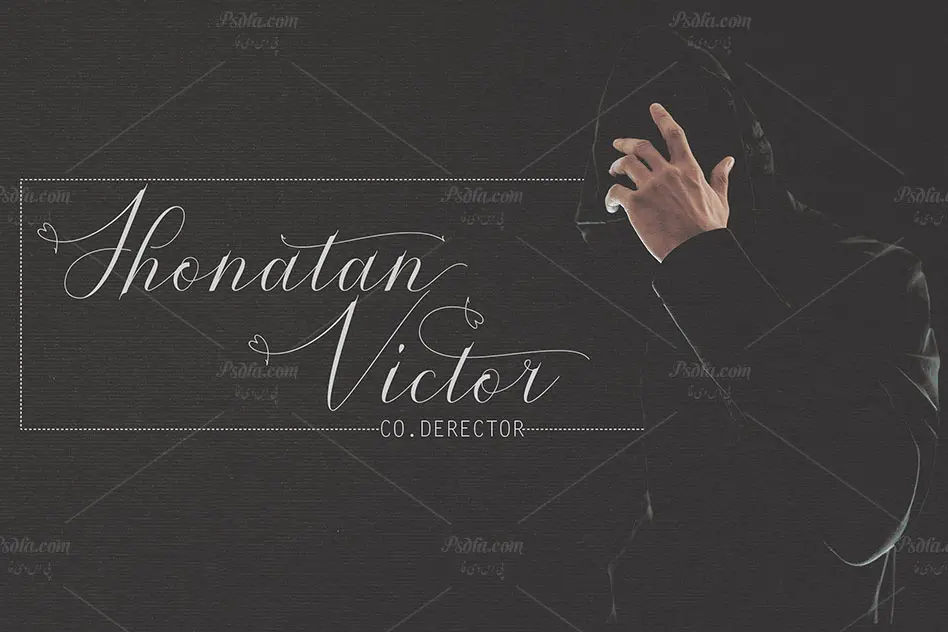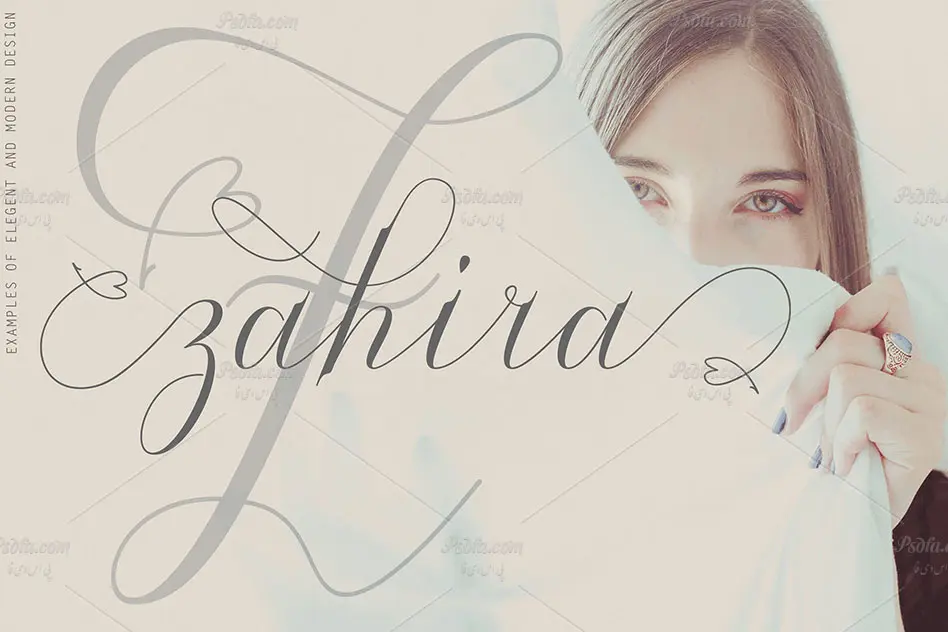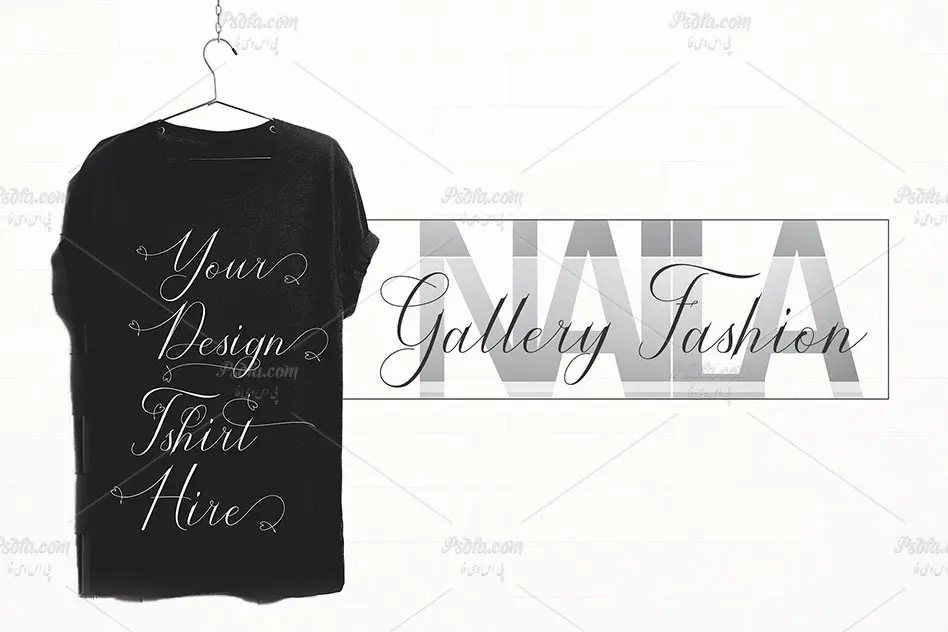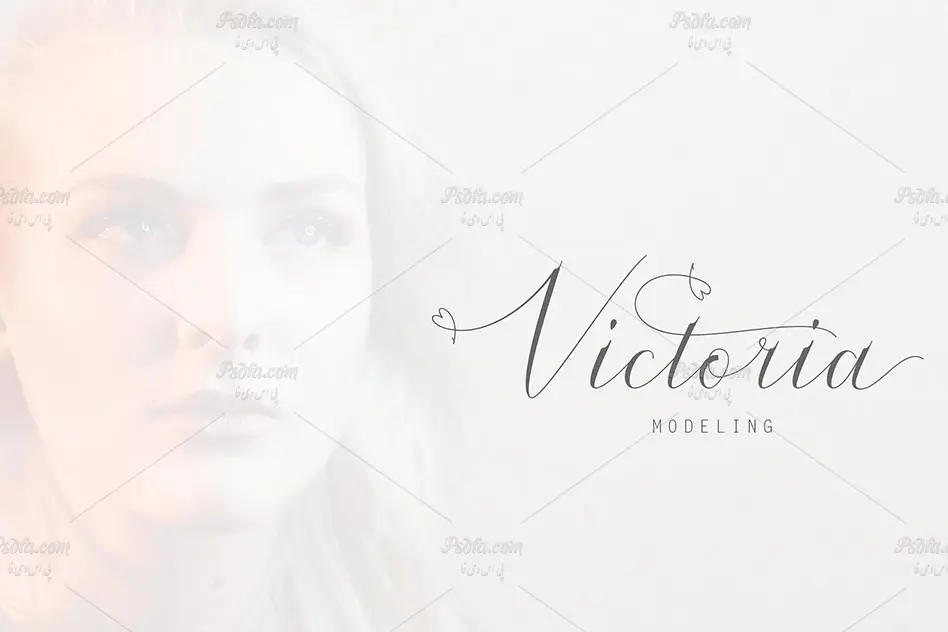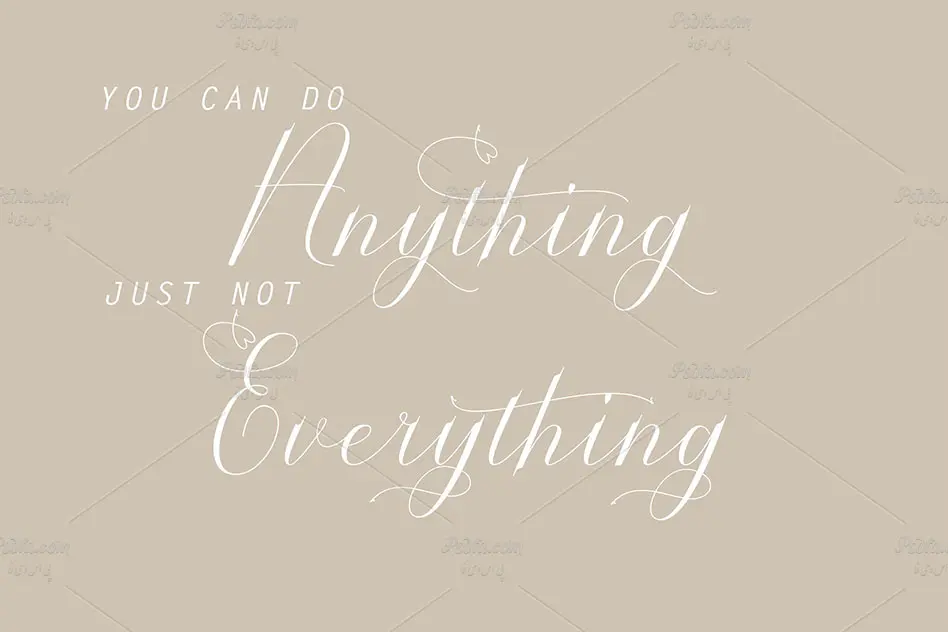
در این پست شاهد فونت دستنویس انگلیسی Serendipity مناسب جهت استفاده در طرح های گرافیکی می باشید. این فونت زیبا در قالب 2 فایل ttf و otf در سایت بارگذاری شده است که با نصب یکی از این دو فرمت در پوشه فونت های سیستم قادر به استفاده از آن در تمام نرم افزارهای گرافیکی و ویرایشگر متن از جمله نرم افزار فتوشاپ ، مجموعه نرم افزار آفیس و … خواهید بود. فونت Serendipity در وزن معمولی (Regular) طراحی شده است که از آن می توان در طرح های گرافیکی همچون طراحی انواع پوستر ، بنر ، تراکت ، بروشور ، کارت تبریک ، کارت پستال ، کارت عروسی و … استفاده نمود. همچنین نسخه وب این فونت نیز در فرمت های eot , svg , ttf , woff و woff2 در فایل فشرده قرار گرفته است که در طراحی صفحات وب می توان از آن استفاده کرد.
- نام فونت : Serendipity